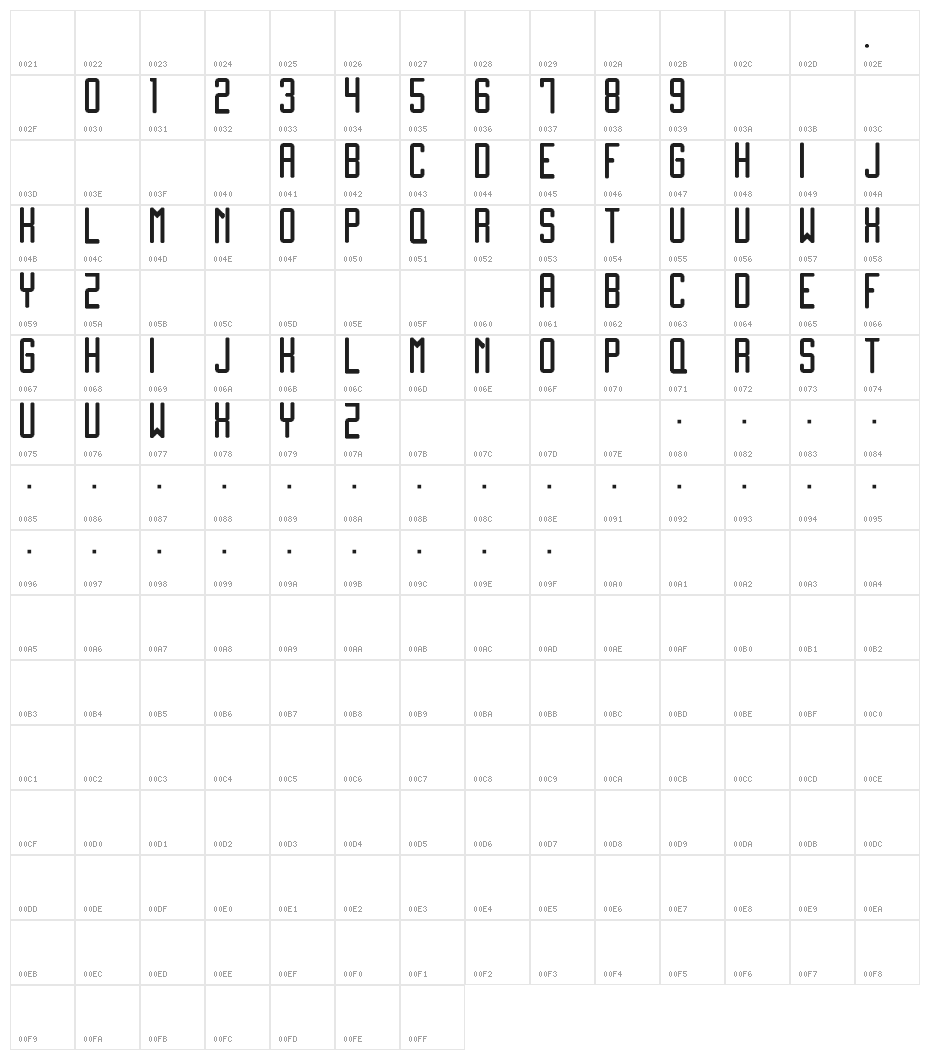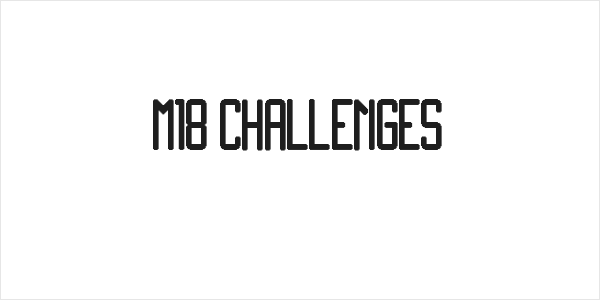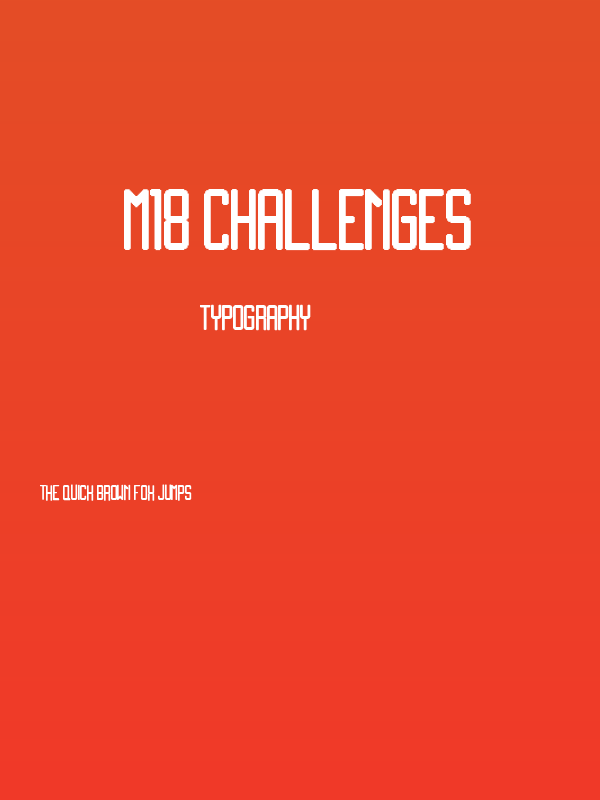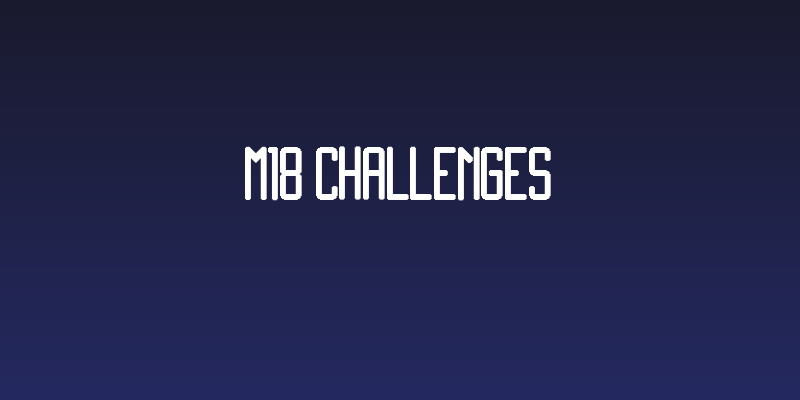
M18_CHALLENGES Font
| Caso d'uso | Logos, Digital displays, Tech-themed projects |
| Progetti proposti | Ideal for tech-themed designs, digital displays, video game graphics, and futuristic branding. |